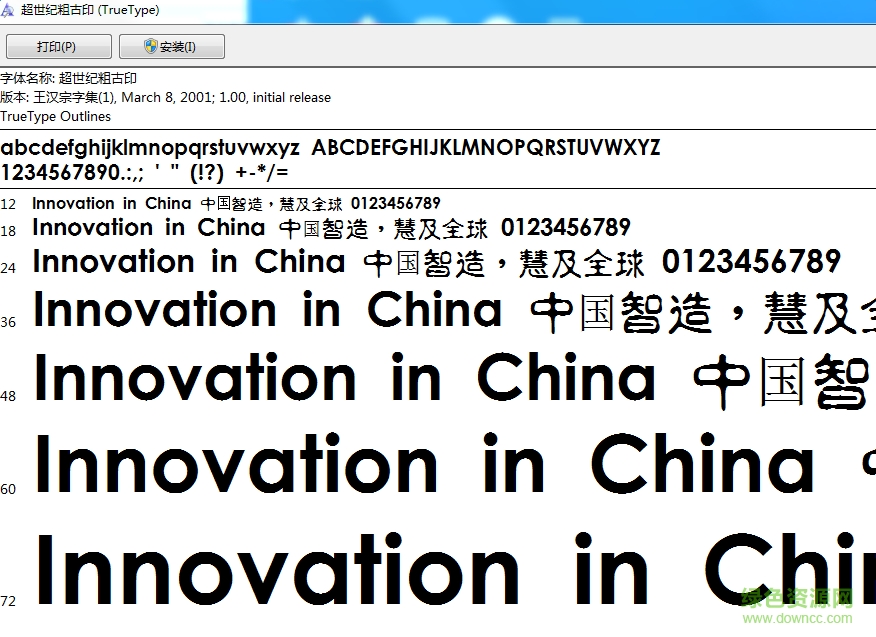
超世紀(jì)粗古印字體是一款為用戶打造的經(jīng)典設(shè)計類印章字體,這個字體非常漂亮,十分美觀,而且這個字體看起來也是非常漂亮的。喜歡的用戶不要錯過哦,更多精彩就在綠色資源網(wǎng)!
于設(shè)計師的創(chuàng)作來說,每種字體都有其各自的特點與風(fēng)格。什么情況下采用什么字體、哪類文字適合哪種風(fēng)格的設(shè)計都比較重要,這也是值得思考的!比如無襯線的文字比較適合現(xiàn)代時尚設(shè)計中、兒童產(chǎn)品的設(shè)計中,粗體比較適合HIPHOP畫面設(shè)計中。有襯線的文字的文字一般運用在傳統(tǒng)類、高端類、莊重類設(shè)計中等等。在設(shè)計中文字最好嘗試一下不同字體所產(chǎn)生的不同感覺。這種感覺需要建立在長期的學(xué)習(xí)、觀察和思考的基礎(chǔ)上。